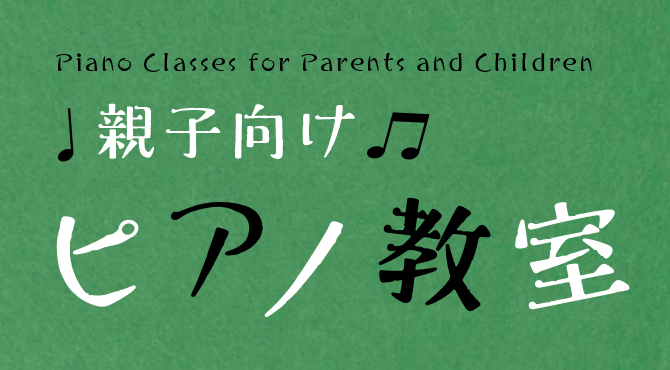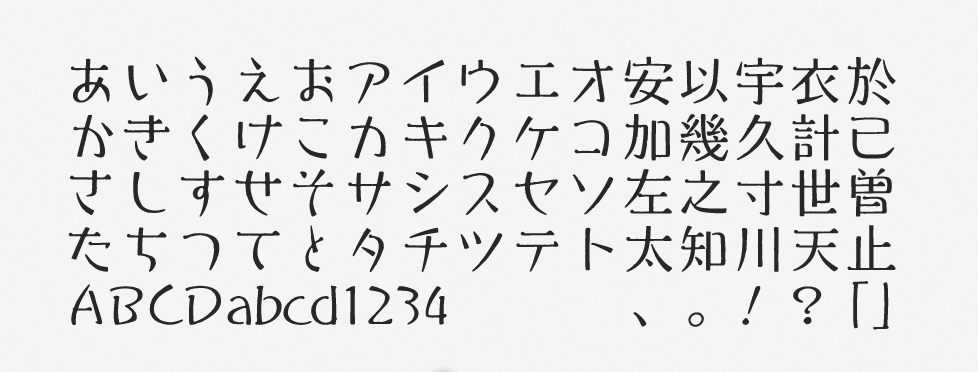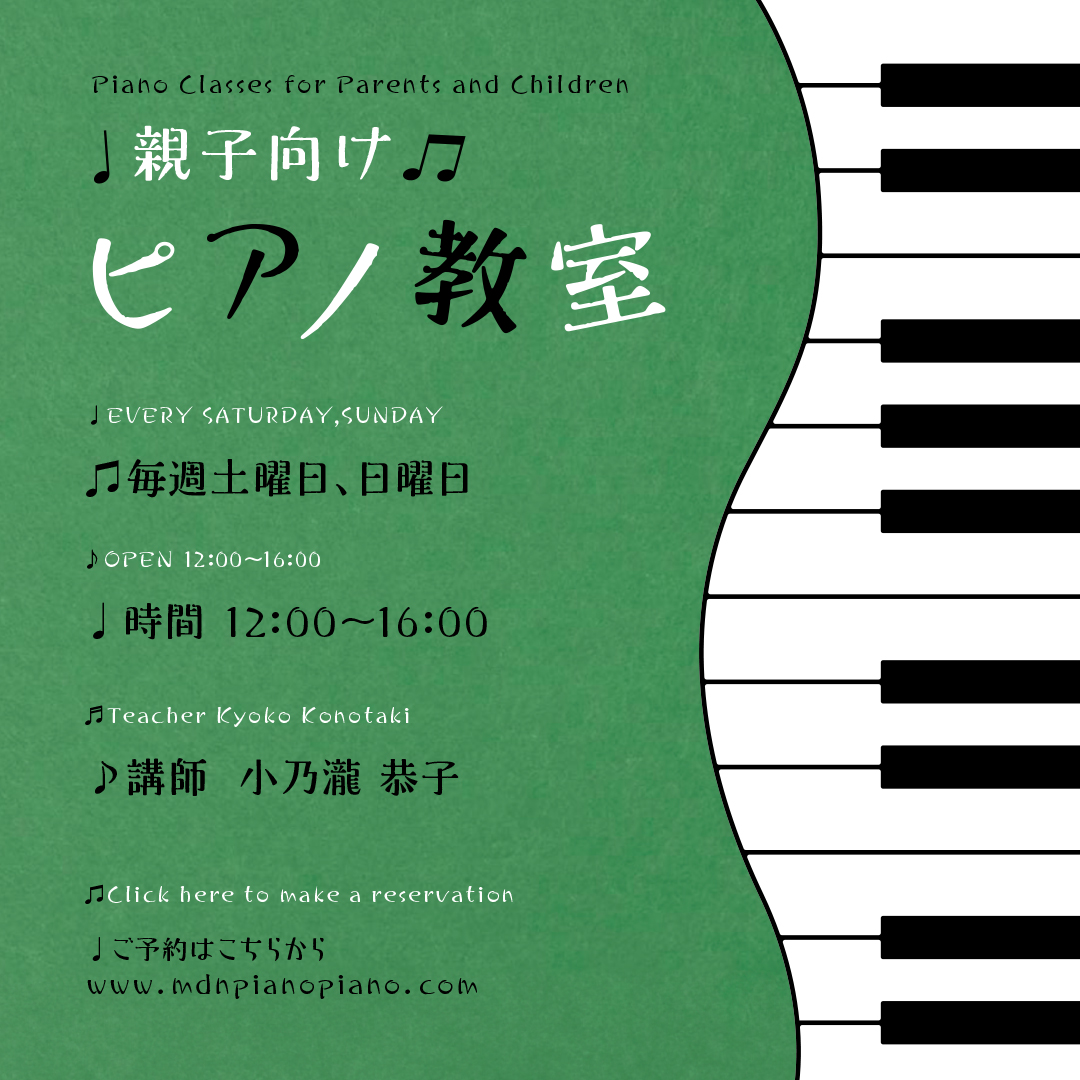
「はせミン」について
はせミンは、2015年の新書体として登場しました。当初からR・M・Bという3つのウエイトが用意されており、遊び心のあるリズミカルなデザインのフォントとして広く活用されています。主にチラシやパンフレットなどでの文字組みを中心としつつ、メッセージを伝えるスタンプのような使われ方もされているフォントです。
「はせミン」の特徴
手書き文字のような雰囲気ですが、明朝体に特有のウロコのようなアクセントを備えているなど、独特なデザインフォントです。漢字の始筆の部分が丸いこともあり、弾むようなポップな楽しさを感じさせます。
線のエッジに手書きならではの「ゆらぎ」があって、柔らかな温かみも感じさせるフォントです。かな文字は特にリズミカルな動きが強調されていますが、漢字の骨格自体はスクエアな設計で、しっかりと可読性も保たれています。
作例はピアノに関する内容のポスターなので、まさにぴったりイメージに合うフォントとして、はせミンを使いました。音符を組み合わせたり、あえて角度を変えながら文字を組んだりすることで、楽しい動きを強調しています。英数字のデザインも個性的なフォントです。